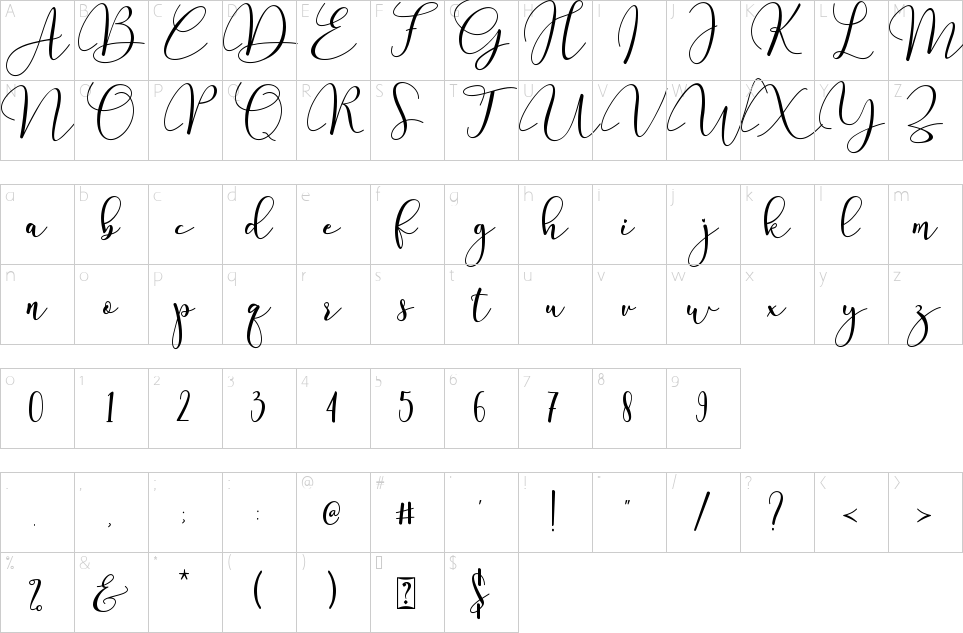
A ‘Valentine & You’ é uma elegante e encantadora fonte que se destaca no seu campo. Desenvolvida por Nox Studio, esta fonte foi projetada para adicionar um toque especial a qualquer projeto gráfico que você estiver desenvolvendo. Com linhas delicadas e cores suaves, ela captura o espírito do amor e da paixão de uma maneira singular. Desde pequenos detalhes como as tramas sutis até os desenhos mais complexos dos caracteres, cada elemento da ‘Valentine & You’ foi cuidadosamente criado para oferecer um acabamento perfeito. Através deste site você pode obter esta fonte grátis e versátil de alta qualidade tanto no Windows quanto no Mac. Com seu design inspirador e sua facilidade de uso, a ‘Valentine & You’ é uma opção ideal tanto para designers como para quem está buscando um elemento especial em seus próprios trabalhos.